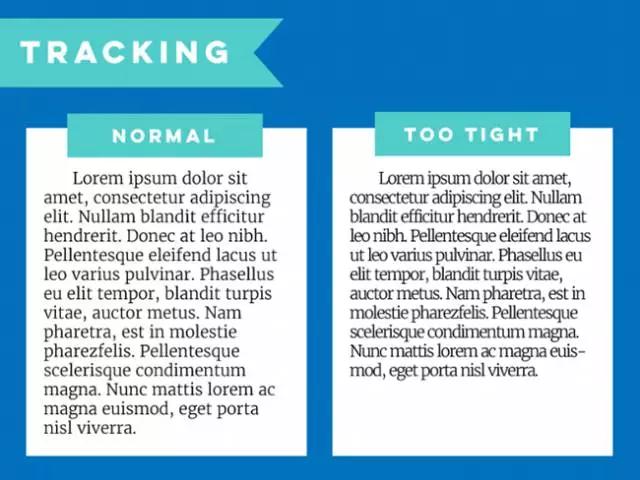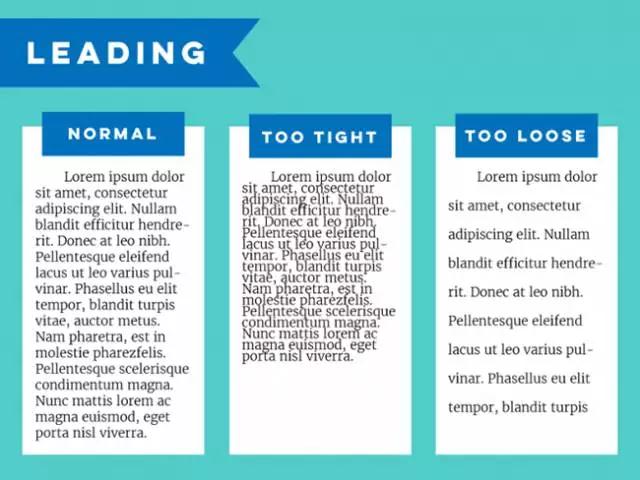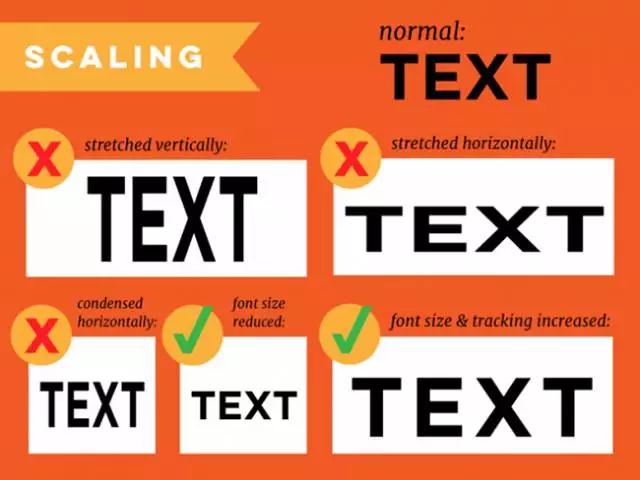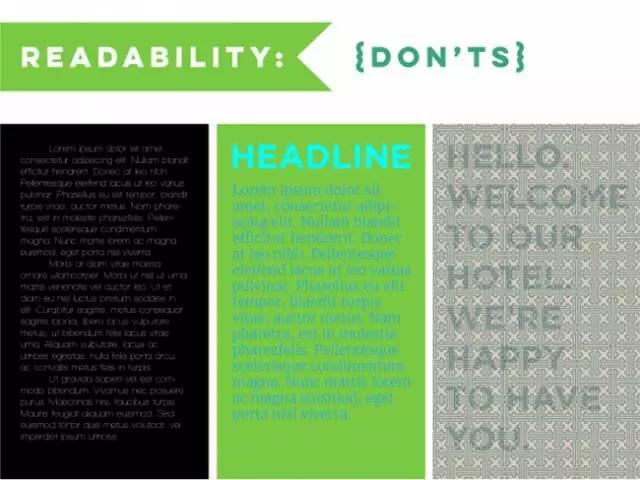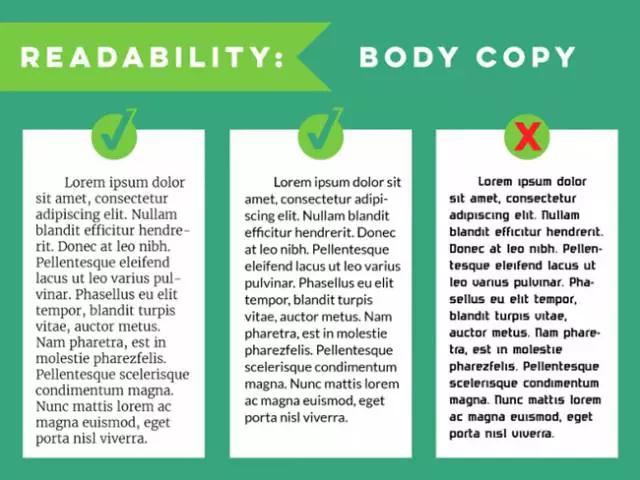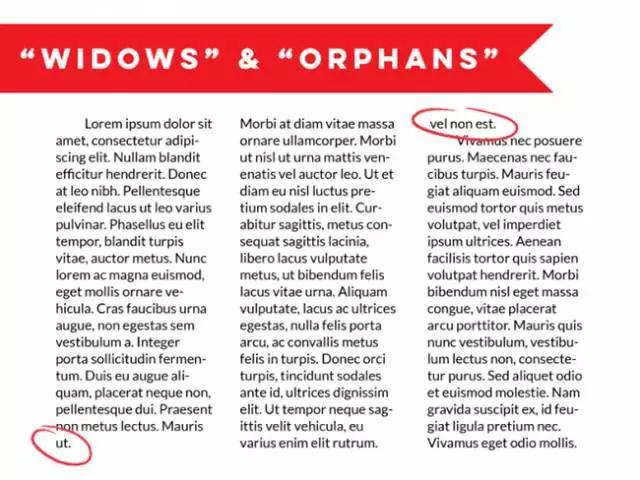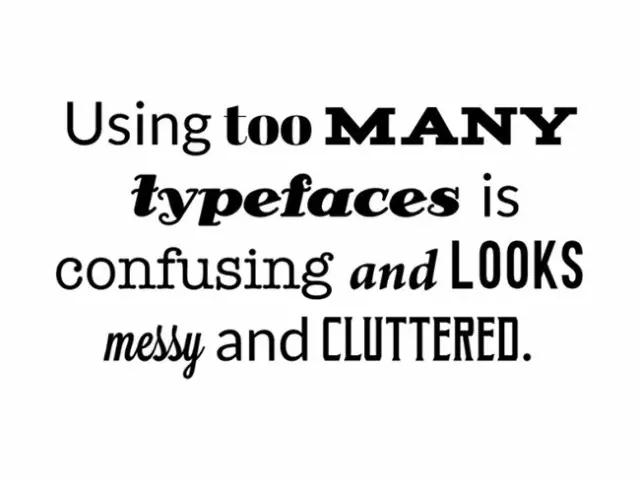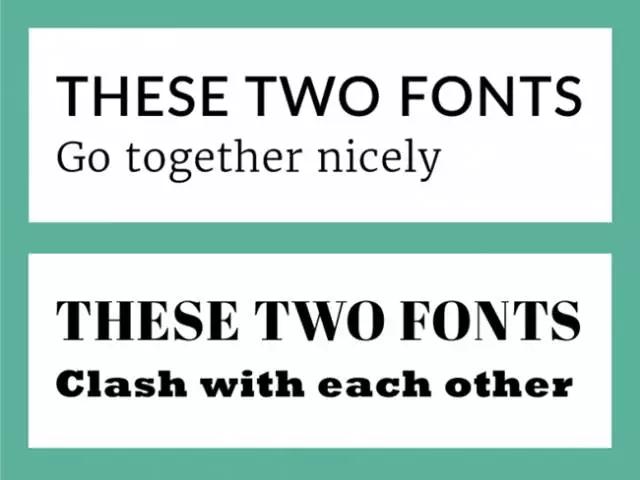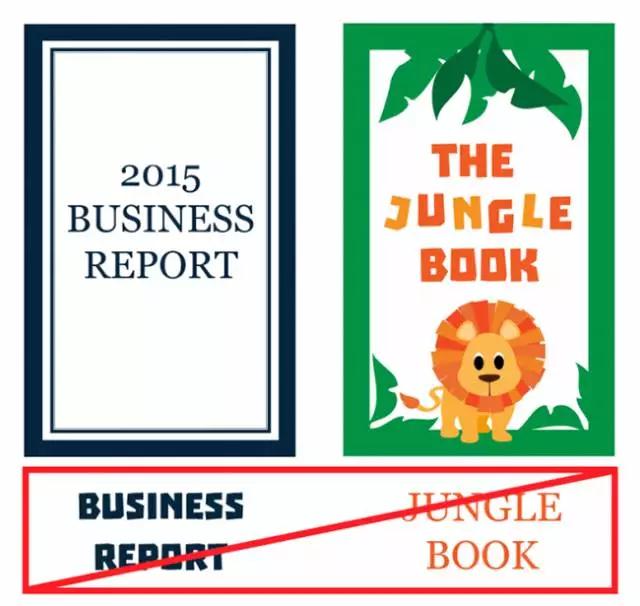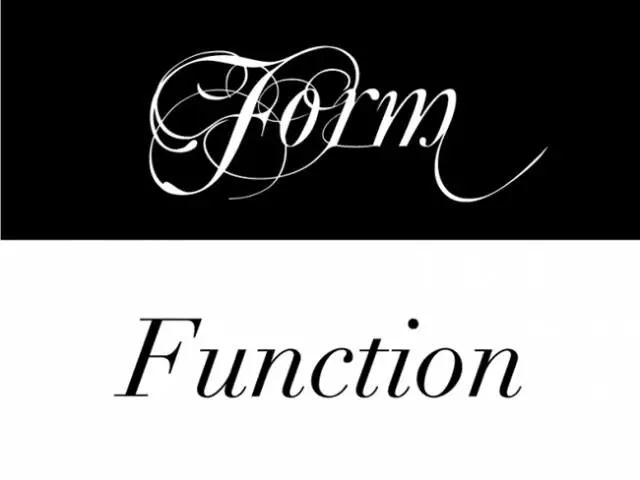
如何做好排版设计,新手常犯的几个排版设计错误
排版是设计中最重要的组成部分之一,它绝不仅仅是将漂亮的字体放在帅气的背景上这么简单。然而,制作优秀的排版并不容易,雷区遍布,稍不注意就流于平庸。过于抠细节容易忽略整体的设计,过于强调视觉又容易忽视功能性,日常的误区之多难以想象。所以,今天我们总结了排版设计中常见的20个误区,帮大家逐个梳理日常设计中容易碰到的排版问题
1、拥挤的文字:字间距
这是很容易忽略的一种错误,字间距过于拥挤会降低文字的可读性。有的字体本身会比较稀疏,或者过于紧密,适当调整至易于阅读的状态即可。
2、密集的段落:行间距
行间距也是影响可读性的重要因素,过于紧凑会难于识别,但是一味地拉开间距在视觉上的效果并不合理。一般行间距是行高的50%左右。
3、不合理的拉伸与压缩
这是另一个常见的错误,图片、文字等元素并没有按照原始比例拉伸或者压缩而造成非正常的扭曲和形变。要避免这个问题并不难,尽量在保持比例的前提下控制长或者宽等单个元素变化,在PS或者AI等软件中,按住Shift键拉伸,在网页设计的时候,尽量按照原始比例来设定元素或者控制单个变量。
4、忽略可读性
正如同上文所说,影响可读性的影响因素很多,不过在诸多问题当中,确保可读性的基础是可读——至少要让人看清元素本身。在黑色的背景上采用白色的字体一般能保证可读性,对比很明显,但是如果字体太过于纤细,视觉上的辨识度就很低了。字体过小、色彩对比度不够、透明度过高都会造成类似的问题,只要你发现难于识别,有针对性地处理即可。
5、文本的阅读舒适度
设计师的排版设计要求当然不能仅仅停留在“可以看清”的程度。标题、宣传语使用加粗的、花式的、装饰性的字体有它的功能性,但是长文的正文部分是需要用户长时间阅读的,要保持阅读的舒适度。字体的尺寸、字间距、行间距都需要细心处理。传统的排版设计中,这个部分更加倾向于使用衬线体,比如中文中报纸上所用的博雅宋就是专门设计的一套字体,衬线,笔画细致干练,高识别度。不过随着设计风尚和需求的改变,目前多用无衬线体,而且需要考虑在不同的设备上的阅读体验,于是有了苹方和思源黑体。
6、“孤儿”与“寡妇”
“Orphans”和“Widows”是印刷排版中的术语,通常指的是行货列、页头和页脚段落最后仅有一两个词构成的短行之类的东西。在文字排版占主体的设计项目中,这些行或者列非常的扎眼,你如果不想让大片的留白打断排版的连续性,最好的解决方案是微调段落宽度、间距。
7、不要在句末双击空格
这种输入习惯在中文中并不多见,但是在英语言国家有不少人会有类似的习惯,在结束一个句子之后双击空格表示结束,但是在今天的排版设计习惯中,通常认为这样的输入方式是过时且不必要的。这种间距在视觉上会影响阅读的流畅性,并且对排版会有影响。保持克制。
8、使用太多字体
这是新手最常见的错误。使用多种字体原本是出于装饰性的目的,但是可控性很差且容易造成视觉干扰,通常将字体类型数量控制在2~3种是比较合理的。不同风格的字体太多会让你的整体风格极其难以统一,专业性就更难以提及了。
9、不匹配的字体
除了不要使用过多的字体之外,还要注意使用协调的字体。不同风格的字体用在一起自然会给人“画风诡异”的感觉,分散用户注意力,降低了信息传递的有效性。字体的搭配手法是介于科学和艺术之间一种存在,它需要你学习排版和字体知识,还需要一部分“设计师的直觉”来支撑。在强调一致性的地方,衬线体和非衬线体不要混用;在海报、封面等地方有的时候需要两种甚至多种类型字体混用,衬线体和非衬线体的搭配就很重要了。多看杂志、网站和杂志排版的案例吧。
10、罔顾内容
选好字体和字体样式很重要,但是麻烦先审视一下你的项目中内容。字体是有情绪的,好玩的、严谨的、浪漫的、随性的、现代的、复古的等等等等。如果字体和设计的情绪与内容不匹配,你会造成脱节和疏离的感觉,这会让观众迷惑。公司报告是严谨的,不要用充满童真的字体或者装饰性字体,充满张力的海报上用日常的普通字体自然也是设计上的失误。
11、形式重过功能
这也是老生常谈。你可以追随近年的设计趋势,找个独特的字体设计一组炫酷而独特的海报或者Banner,做的非常的艺术。但是这样的设计可能会存在阅读障碍,读者需要耗费很长时间来分辨它的内容,那么这就是明显的形式重于功能了。如果你决定这么设计的话,最好平衡一下艺术性和可读性——也就是它的功能性。
12、过度强调
有时候你需要强化某个部分,会在视觉上进行强调,让它从整个设计中脱颖而出。文字部分常见的手法很多,斜体、粗体、下划线、大写、增大字体大小,等等。但是千万不要将所有的强调方式都用在同一篇文字同一个段落中,这样会让它看起来凌乱不堪。
13、全用大写
同样,这是一个在英文情况下常见的设计误区。在标题中全用大写,这个没问题,段落中如果偶有需要强调的地方用大写也说的过去。但是在此之前,要保持约定俗成的最基本的使用习惯:标题大写,正文小写。
14、忽视层次结构
在排版中,层次这个词是区分文本和不同元素的重要性区别的学术性说法。以我们所熟知的报纸为例,标题阐述核心,尺寸最大,文字大写,粗体强调,其次是副标题,字体小点,文字不再大写,再其次是正文,字体最小。如果打破了这种层次结构,用户会迷惑。哪个重要哪个其次,傻傻分不清楚。
15、不对齐
设计原则中,对齐是最重要的几项之一。对齐会让文字排列有序而合理,视觉上统一而一致。不同的对齐方式混合在一起会产生随机的间距,难看且阅读困难。
16、使用对齐工具
想要让排版对齐最好的方式就是打开软件的对齐工具,现在的排版和作图工具都有相关的对齐辅助工具,在它们的辅助下让你的排版更加整齐吧。
17、粗糙的边缘
这种问题在英文排版中更常见一些,中文排版中这种问题实际上并不严重,诸如Office一类的工具会自动帮你微调,而更专业的排版软件中也有相应的算法帮你解决。英文排版中这种问题更多,需要你细心处理调整,实际上这并不是什么特别复杂的事情,重要的是细心。
18、添加特殊效果
一般添加特效是个不错的思路,但是必须使用得应景。许多自带的字体特效,诸如3D字体、大阴影、扭曲特效,都很容易让设计看起来廉价而过于花哨。多看时下流行的设计范例,克制随意添加特效的冲动。
19、在重要项目中尝试新效果
在重要的项目中测试新的设计手法、特效和有趣的字体并不是一个靠谱的方案,也不是合适的时机,甚至不是一个专业设计师应该做的事情。这种手段过于冒险,因为新的手法极有可能并不实用可靠,如果你相信自己的直觉也应该在其他的非重要项目中进行试错。
20、忘记审核
设计需要严格把关,做完设计之后不审核是不负责的行为。设计完之后,最好通读全文,做拼写检查,确保没有语法错误、印刷错误,这也是设计的一部分。